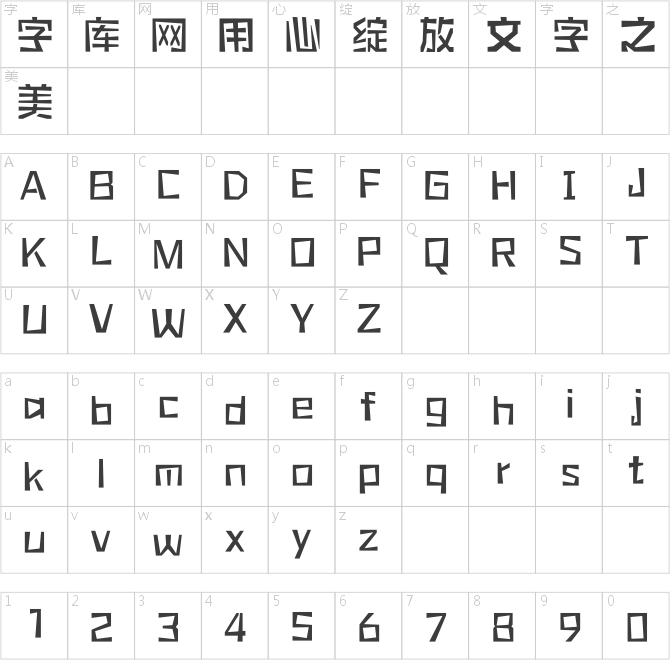
方正橡皮章体 简
中国汉字给人的感观印象是“方块字”,即在一块面积大小相等的空间内,刻画出一个个独立的汉字。比如古代的“活字”雕刻,近代的机械打字机“字盘”。单字之间看似毫无关联,可组合在一起,就能体现出正负空间的强烈对比,方阵严整。 该字体笔画的安排,沿袭着橡皮章雕刻特有的平直、硬朗,打破传统的“横平竖直”,增加字体的动感,有古老石碑的拓印之风,不失时尚潮流的文艺之美,无论是横排或竖排,行列之间整齐有序,给人予方块拼接,搭积木之美感,可广泛用于报纸、杂志、包装、广告等印刷品的标题、正文。